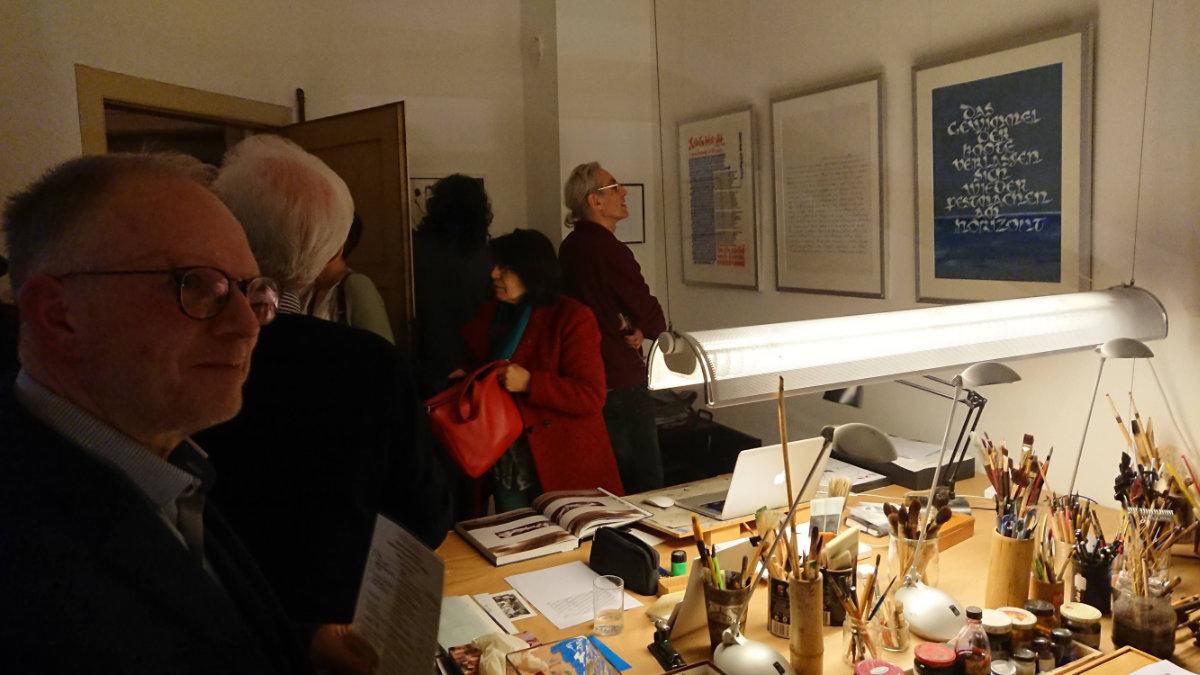
Federlesen
Ausstellung der Kalligraphien von Hubert Leonhard Graf im Schrifthof
Impressionen von der Vernissage
18. Januar bis 15. März 2020 zeigen wir die Ausstellung im Schrifthof mit vielfältigen Werken seiner Handwerkskunst. Er gibt mit seinen Kalligraphien einen Einblick in sein Schreiben mit der Feder und allen artverwandten Werkzeugen. Vom klassisch schön gestalteten Text bis hin zu experimentellen Schriftbildern, mit denen er die Gedanken und Aphorismen von Schriftstellern und Künstlern inszeniert.